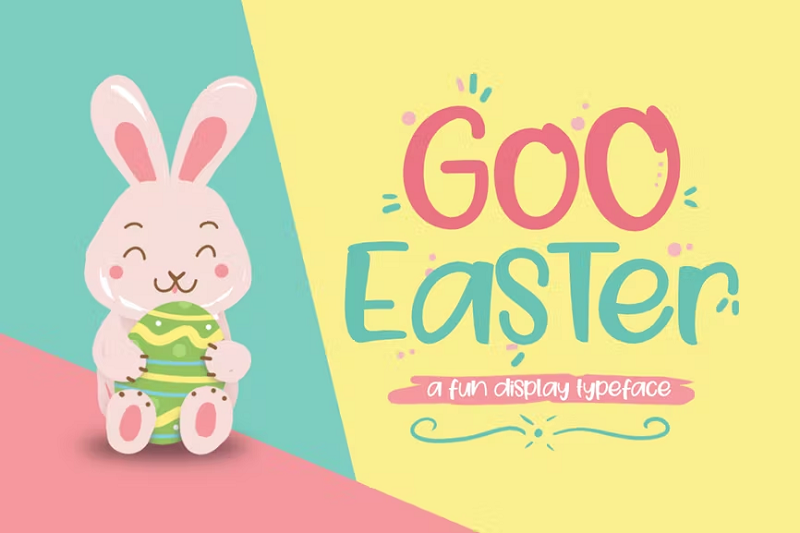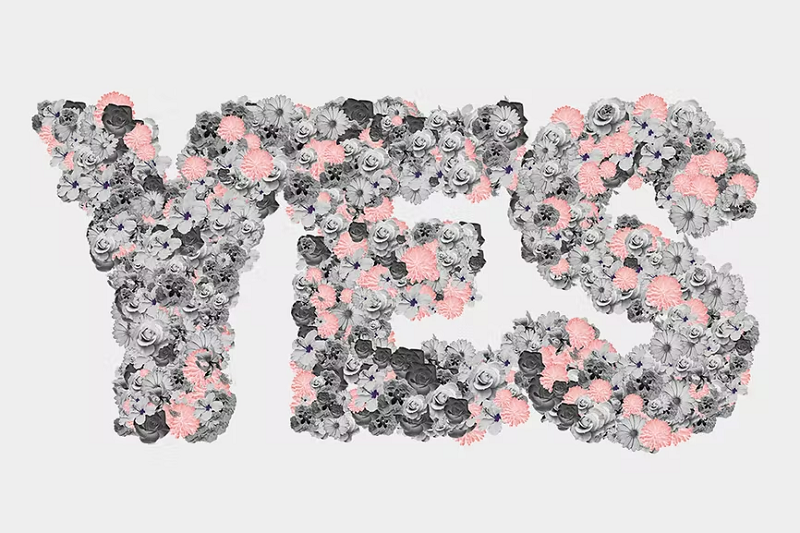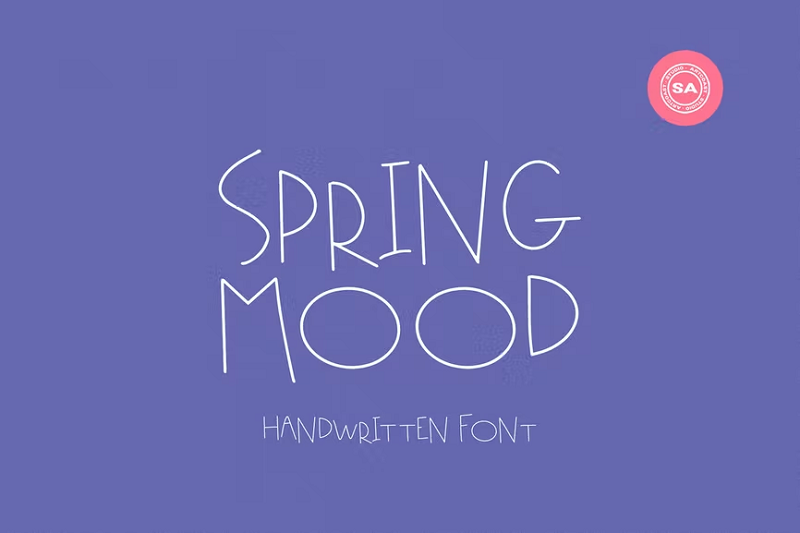
Publié: 2022-08-01Le printemps est la saison des nouveaux départs, alors pourquoi ne pas insuffler une nouvelle vie à vos créations avec ces magnifiques polices printanières ?
Toutes les polices de printemps de ce tour d'horizon ont été soigneusement sélectionnées. Ils évoquent bon nombre des mêmes représentations que nous associons au printemps, comme les fleurs fraîches, les plantes qui poussent, les lapins de Pâques et le réchauffement climatique.
1. Dimanche de printemps
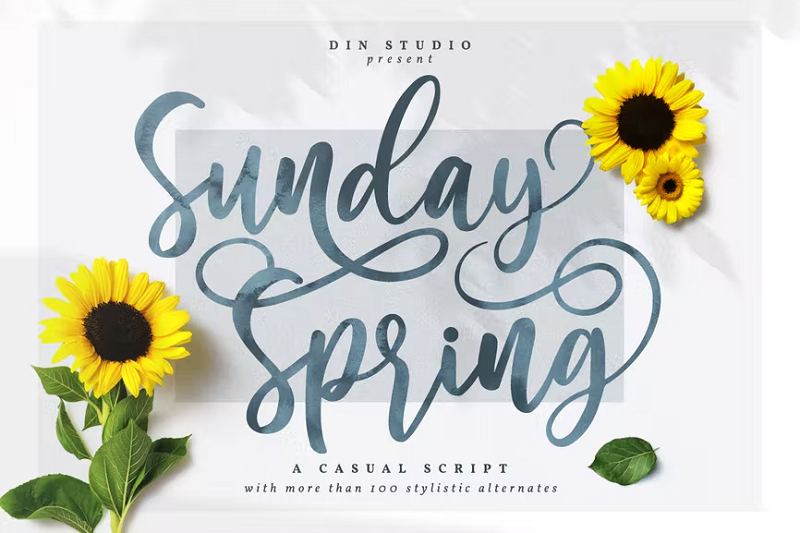
Sunday Spring est une police de script décontractée parfaite pour tous vos designs sur le thème du printemps. Il est élégant et courbé et ne manquera pas de donner une touche féminine à vos créations.
Pourquoi c'est notre premier choix
C'est facile à lire, délicat et super élégant. Cette police aurait fière allure sur à peu près n'importe quel design et évoque vraiment ce sentiment printanier.
2. Bonjour printemps
Hello Spring est un script amusant et fantaisiste qui aurait fière allure sur des affiches ou des produits physiques comme des t-shirts, des tasses, etc. Cette police en gras est super lisible et serait la police parfaite pour les en-têtes. Le pack de polices comprend des caractères majuscules et minuscules ainsi que des chiffres et des signes de ponctuation.
3. Printemps frais
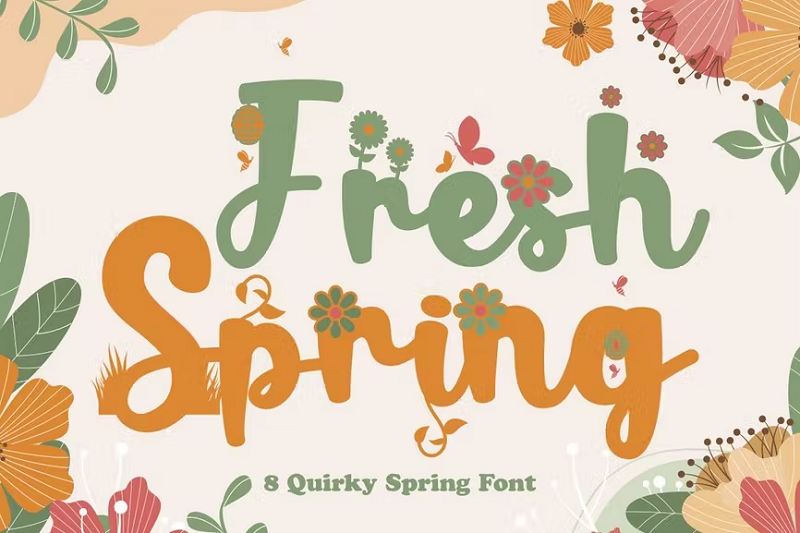
Fresh Spring est une police printanière unique et originale conçue pour les plantes et les éléments botaniques. Le pack de polices comprend 7 versions différentes de la police avec différents styles de fleurs et de feuilles. Cette police amusante est parfaite pour les motifs à thème floral.
4. L'amour est le printemps
Love is Spring est une police unique dessinée à la main, parfaite pour créer des designs accrocheurs. Chacune des lettres comprend un cœur monoline et des inserts tourbillonnants qui donnent au script une sensation fraîche et florale. Cette police aurait fière allure sur les cartes de vœux pour la fête des mères, la Saint-Valentin, Pâques, etc.
5. Amoureux des lapins
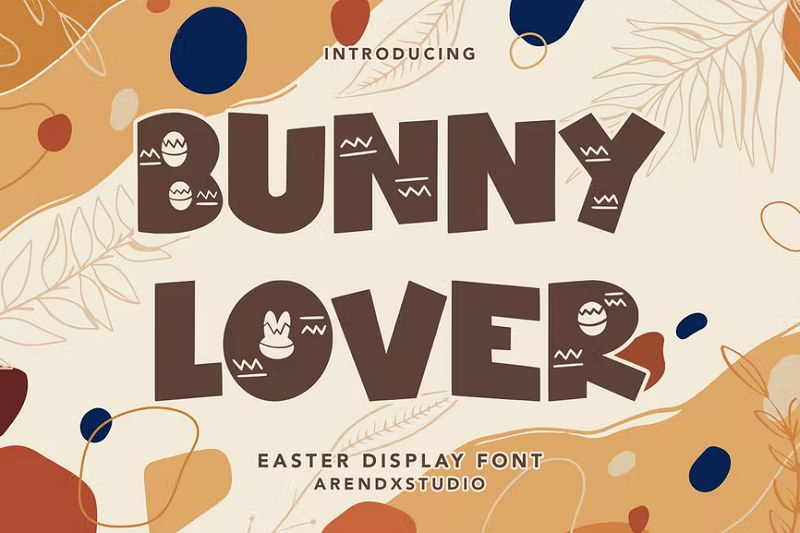
Bunny Lover est la police d'affiche parfaite pour votre prochaine chasse aux œufs de Pâques. Cette police de caractères sur le thème du lapin est audacieuse, accrocheuse et super amusante. Les personnages comprennent des gribouillis amusants, des œufs de Pâques et des motifs de lapin. Le téléchargement de la police comprend des caractères majuscules et minuscules, des chiffres, des symboles et des signes de ponctuation.
6. Egster
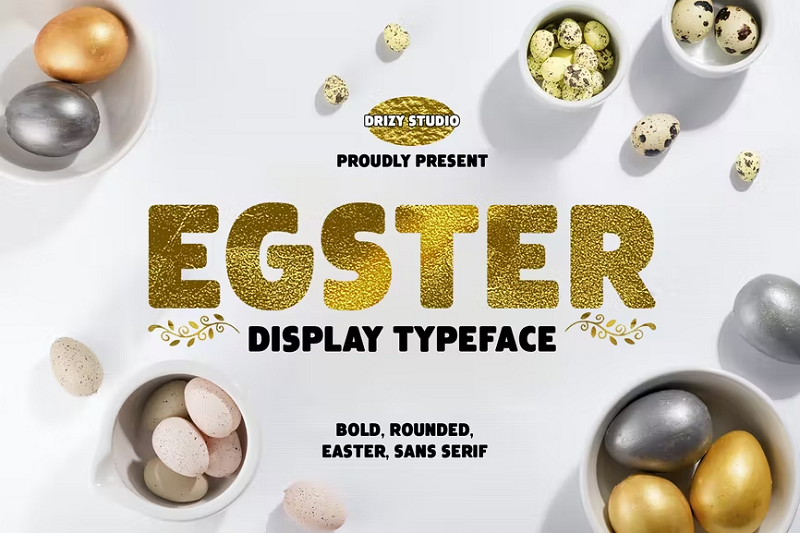
Egster est une police d'affichage audacieuse parfaite pour toutes vos conceptions de Pâques. Cette police simple mais élégante évoque tout le plaisir de Pâques et serait parfaite pour les cartes de vœux, les invitations, etc. C'est amusant, volumineux et facile à lire, ce qui en fait un excellent choix pour les conceptions destinées aux enfants.
7. Sakura Kei
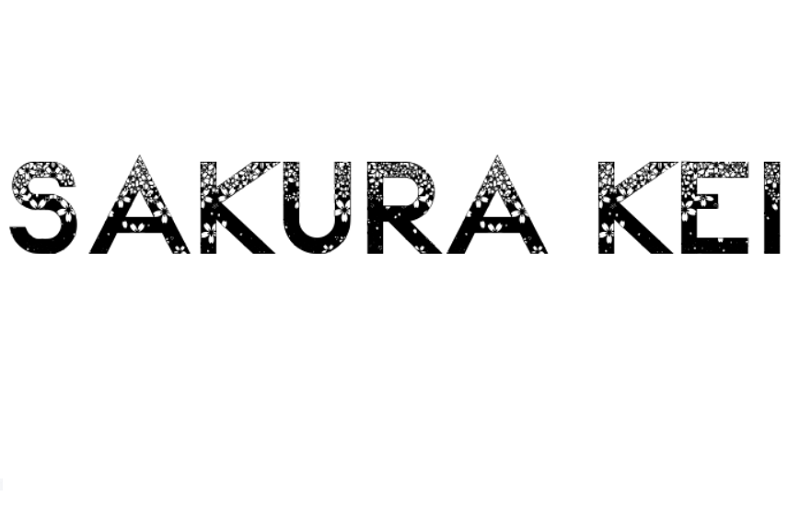
Sakura Kei est une police audacieuse et accrocheuse inspirée de la calligraphie japonaise. La police présente un motif unique de fleurs de cerisier Sakura, une fleur synonyme de printemps au Japon. Cette police gratuite aurait fière allure dans le cadre de conceptions numériques.
8. Bonjour printemps 2
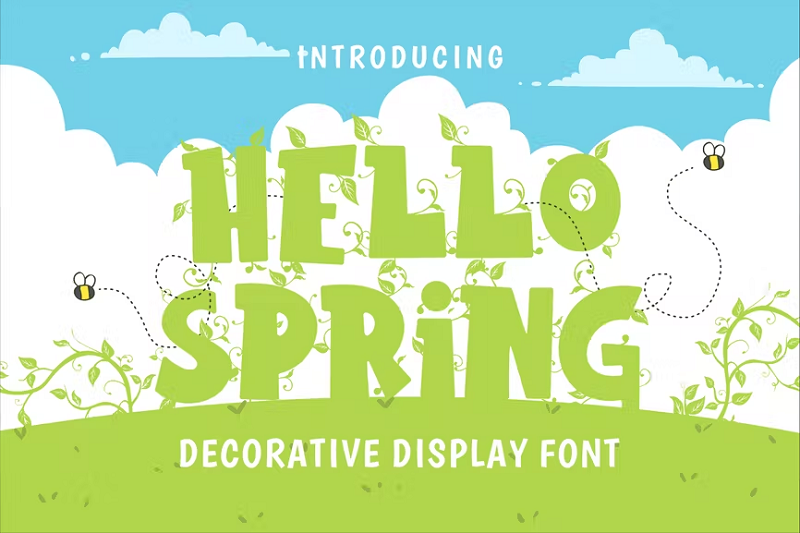
Hello Spring 2 est une police d'affichage décorative qui aurait fière allure sur des affiches et dans le cadre de conceptions numériques. Cette police de caractères amusante d'inspiration botanique est audacieuse, attrayante et facile à lire. Le pack de polices comprend des lettres et des symboles ainsi que des caractères spéciaux inspirés des feuilles.
9. Comba
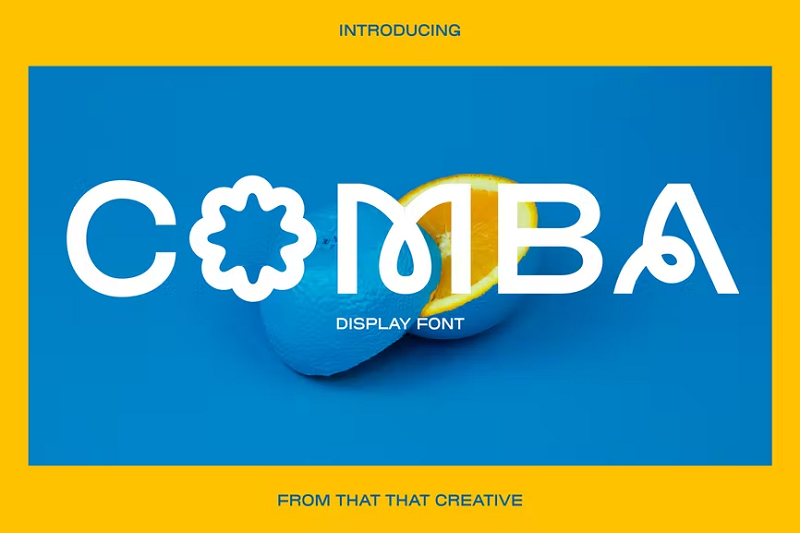
Comba est une police d'affichage super unique qui serait parfaite pour les t-shirts, les tasses et d'autres types de marchandises. C'est l'une des polices de printemps les plus créatives que nous ayons vues, avec des caractères très stylisés qui sont encore assez faciles à lire. La police est entièrement en majuscules et le téléchargement comprend des lettres, des chiffres, des signes de ponctuation et des flèches.
Penser au symbolisme
Le printemps symbolise beaucoup de choses. C'est la saison au cours de laquelle les animaux en hibernation se réveillent et les fleurs commencent à fleurir, mais c'est aussi la saison de Pâques, du nettoyage de printemps et de nombreux festivals et célébrations.
Choisissez une police qui symbolise les aspects spécifiques du printemps que vous espérez capturer dans votre conception. Par exemple, pour les motifs de Pâques, choisissez une police sur le thème de Pâques.